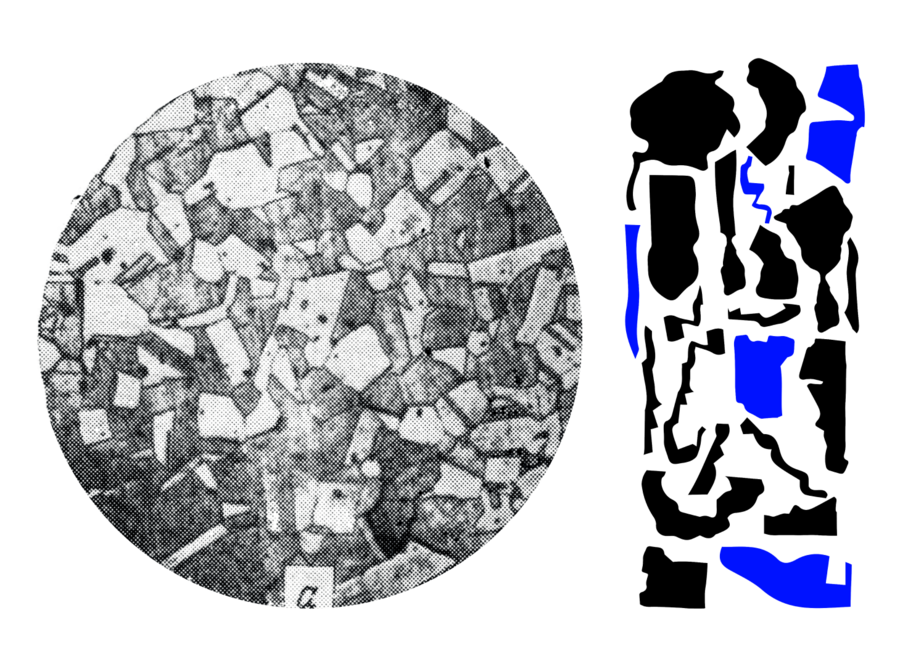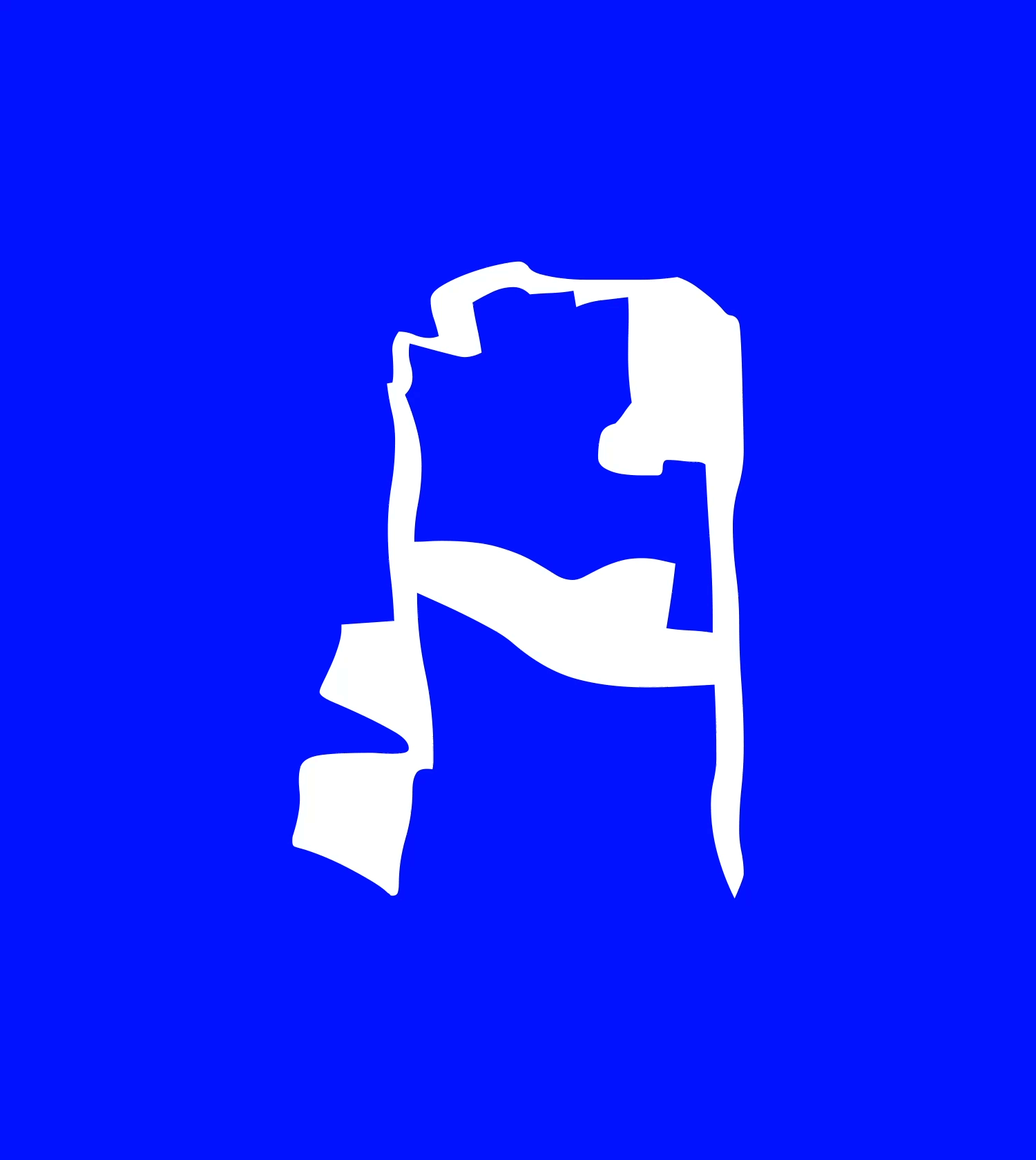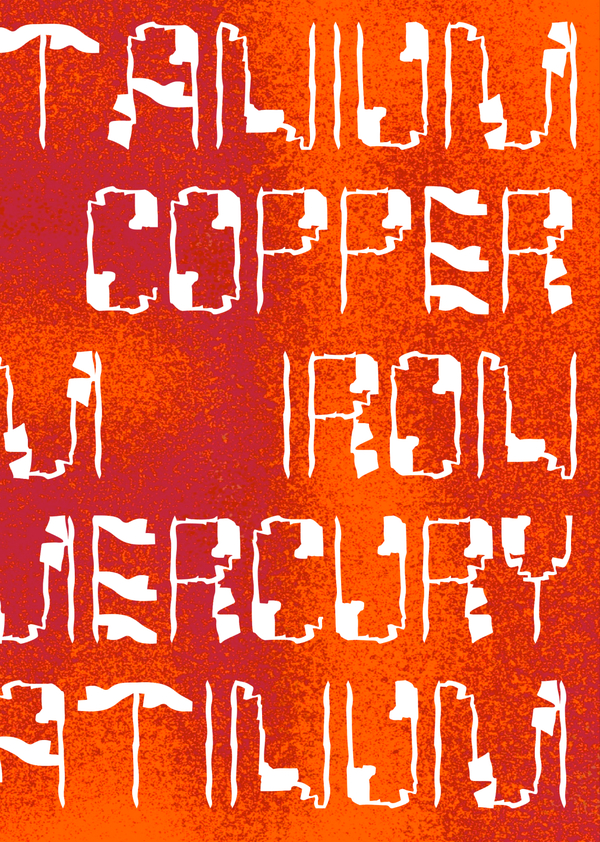
Metalscope — модульный шрифт, геометрия которого рождена из изучения микроструктуры металла. Название объединяет «металл» и «микроскоп». Каждый знак собирается из повторяющихся модулей, что создает ритмичную
и цельную графику. Шрифт подходит для айдентики, заголовков и типографических экспериментов.